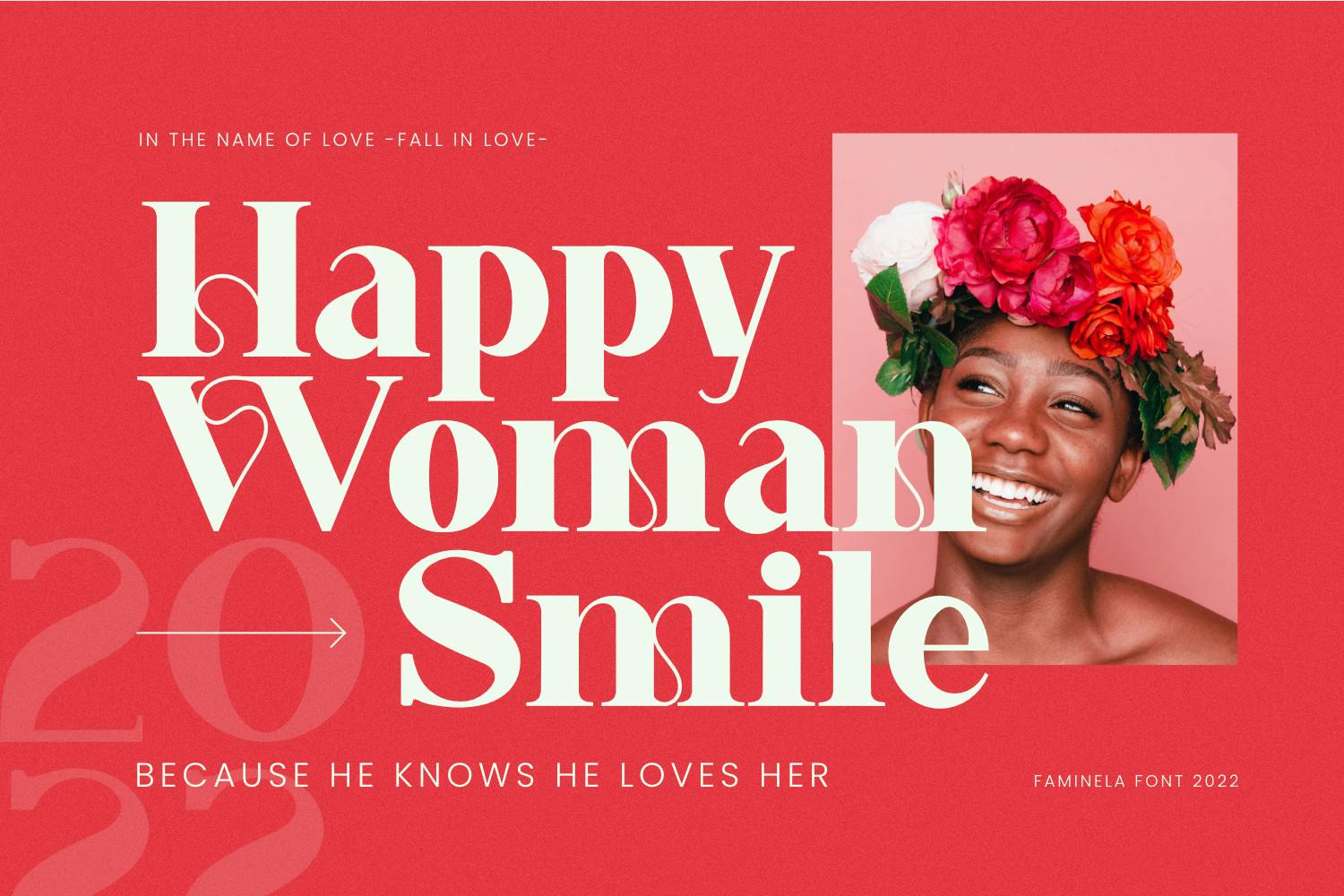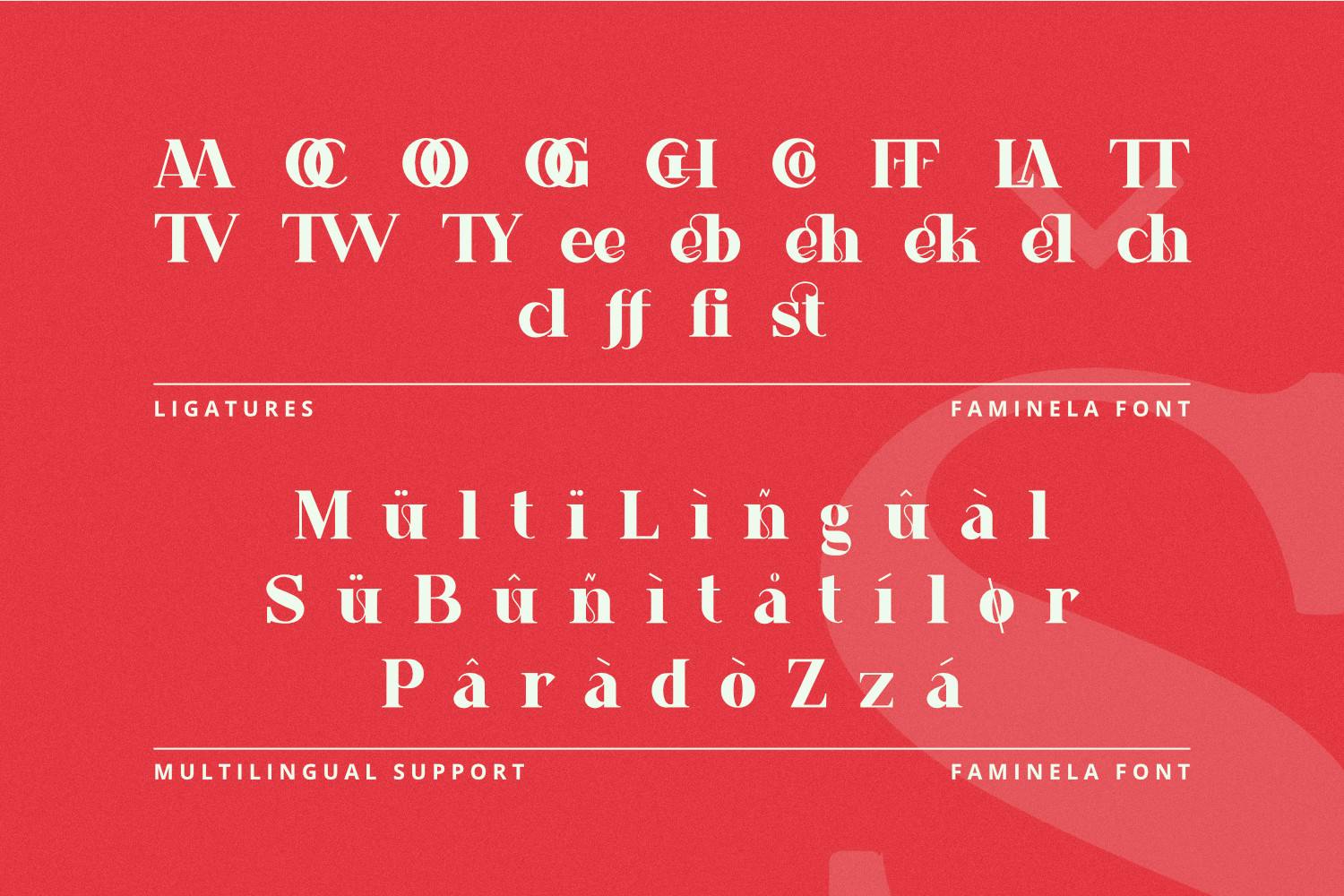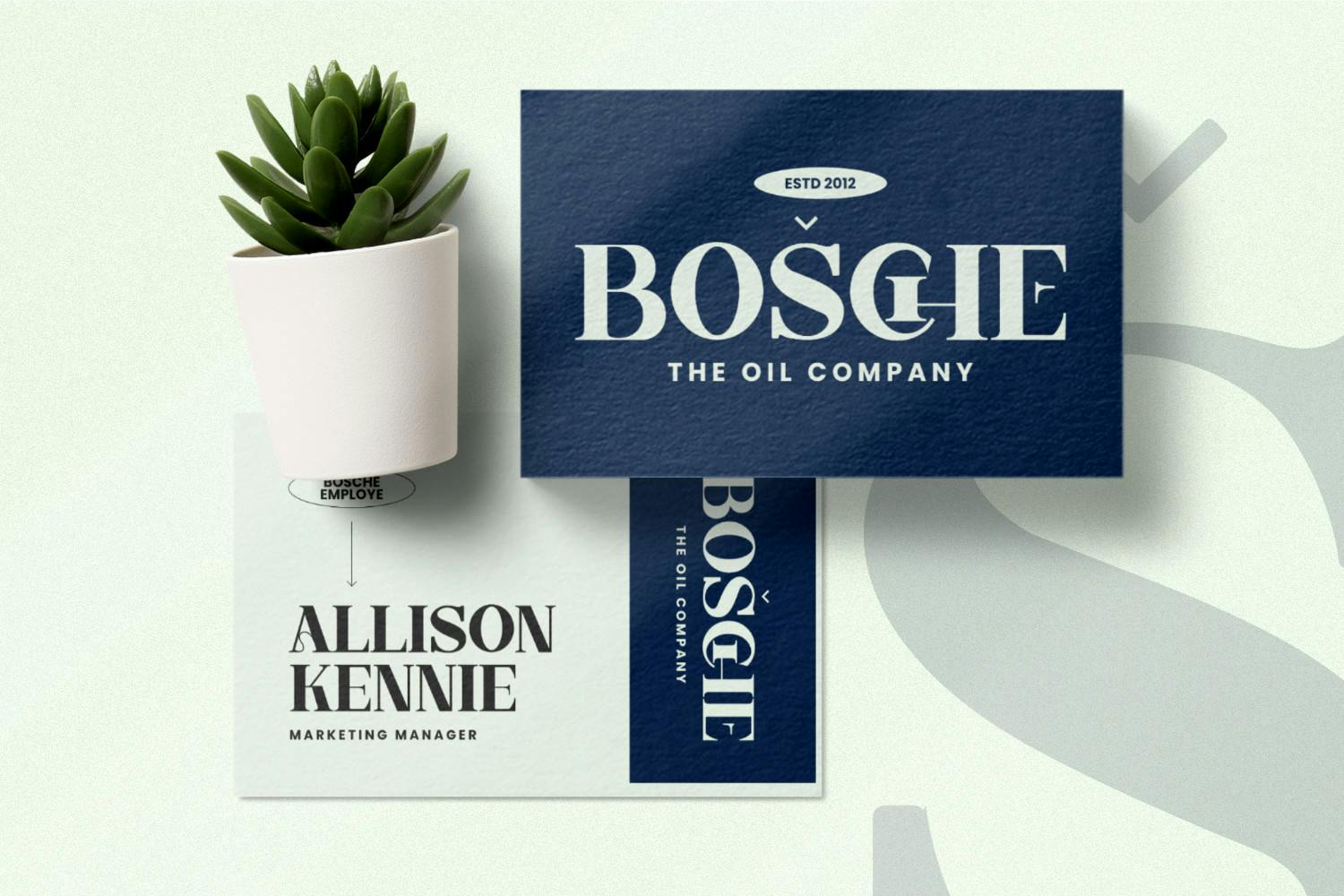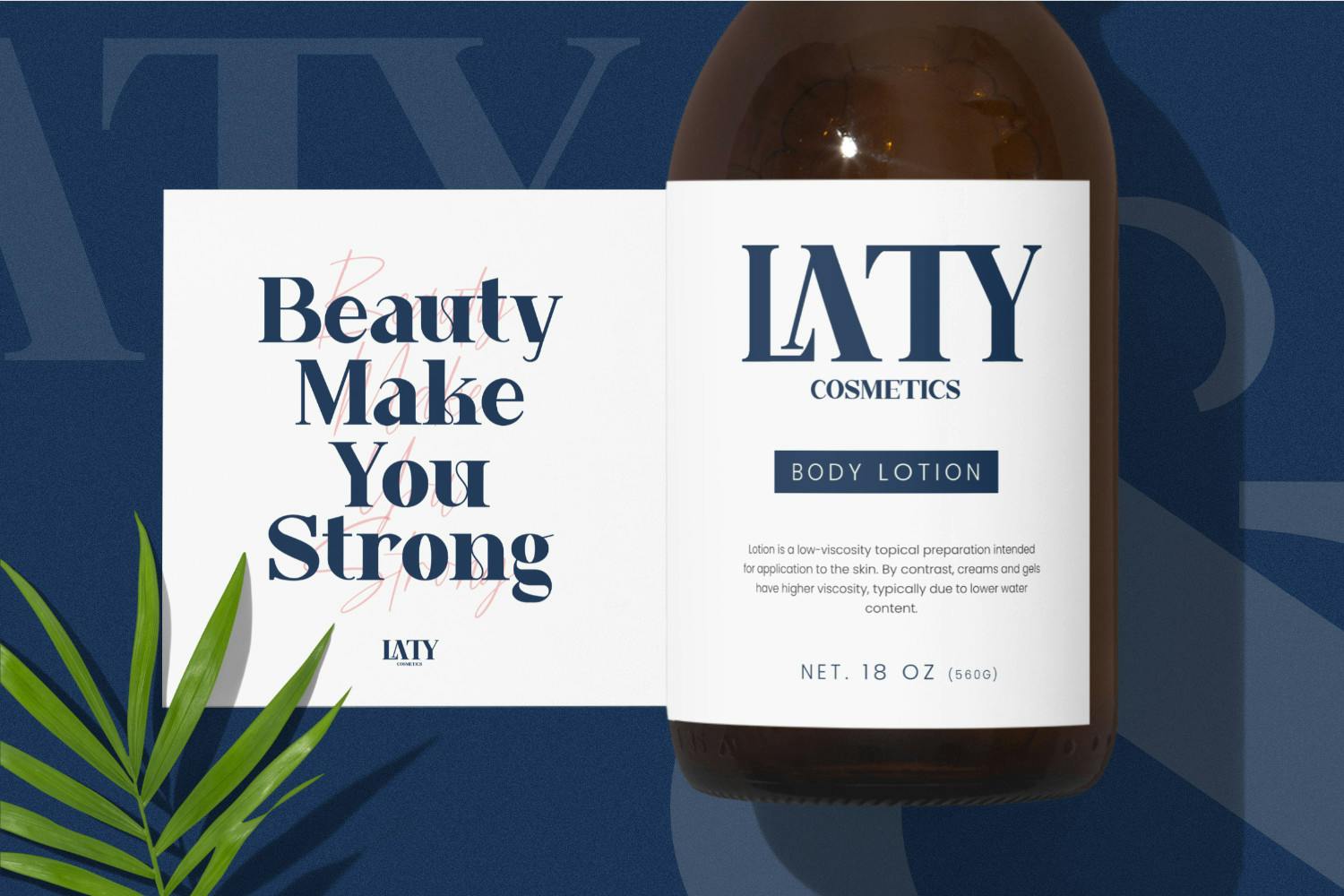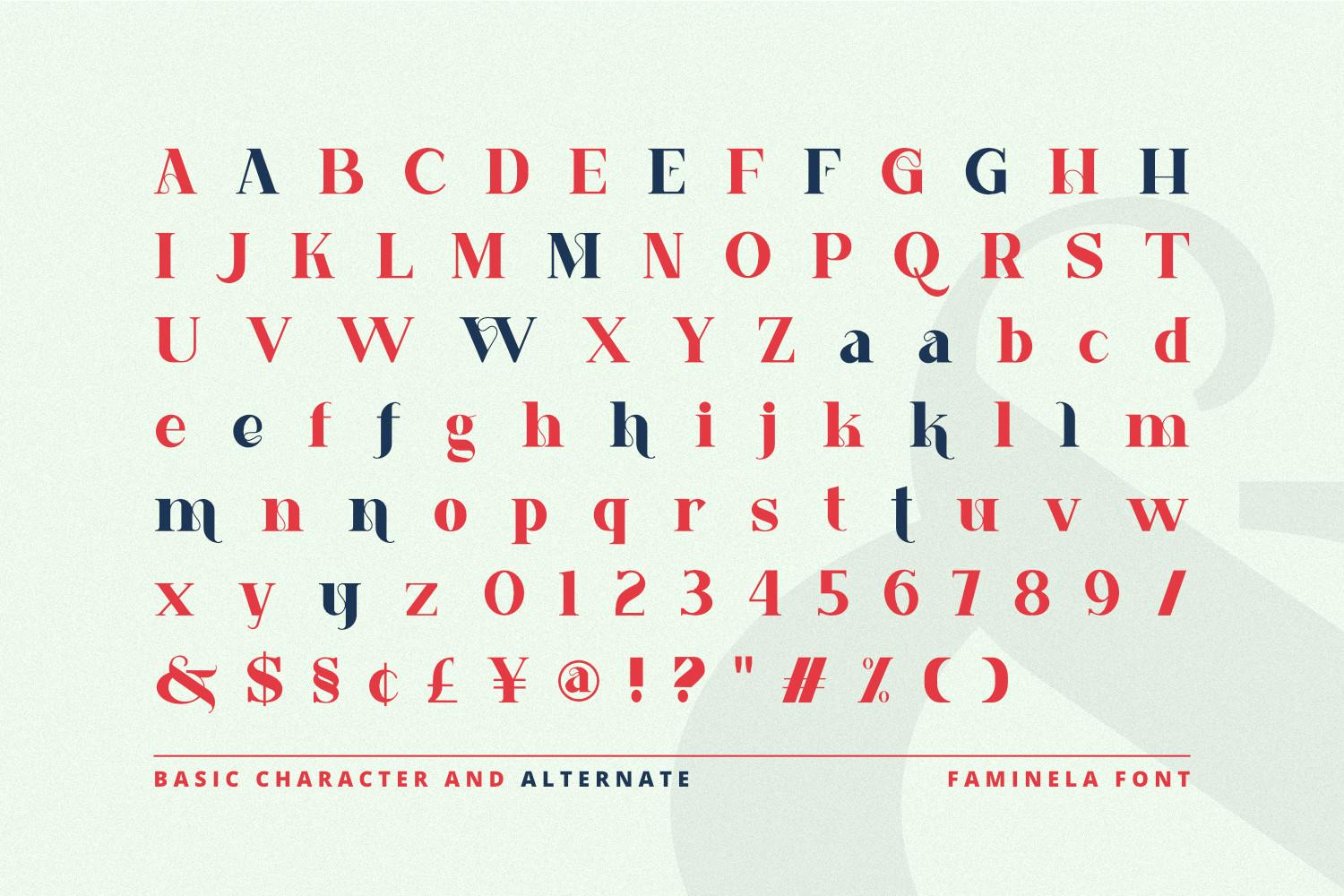
محصول فونت Faminela برای بسیاری از پروژههای شما مانند لوگو و برندینگ، عکاسی، دعوتنامهها، واترمارکها، تبلیغات، طراحی محصولات، لوازمالتحریر، طراحی عروسی، برچسبها، بستهبندی محصولات، رویدادهای خاص و بسیاری موارد دیگر مناسب است.